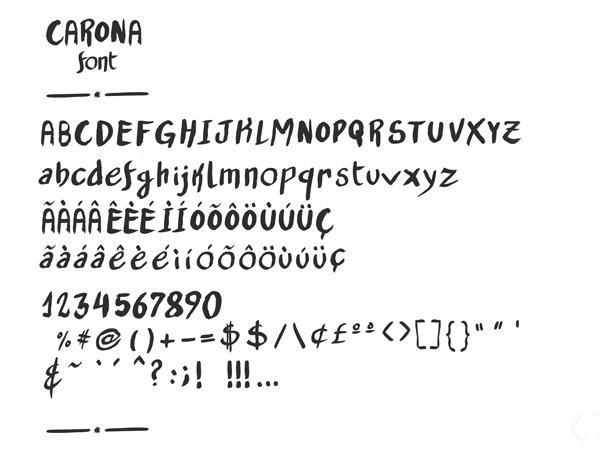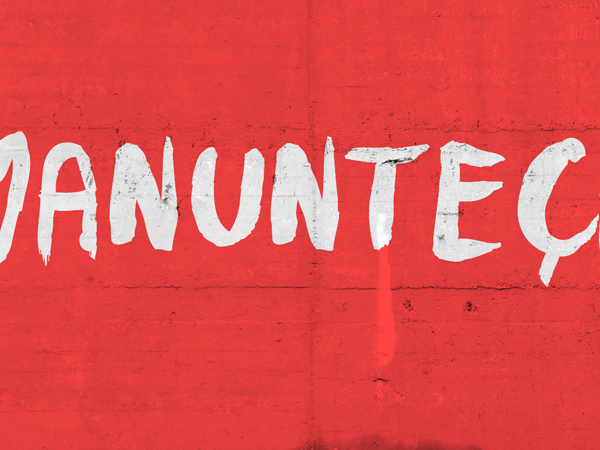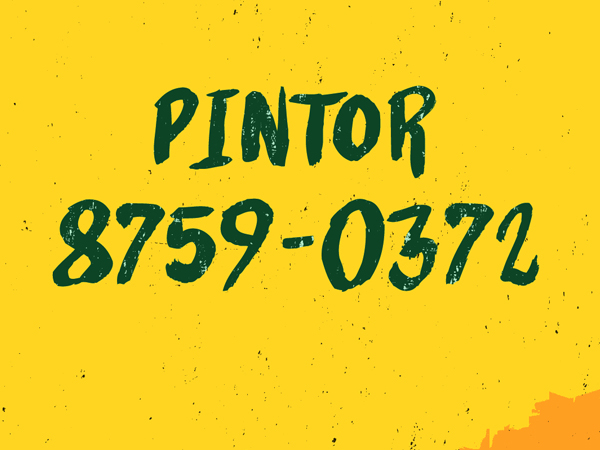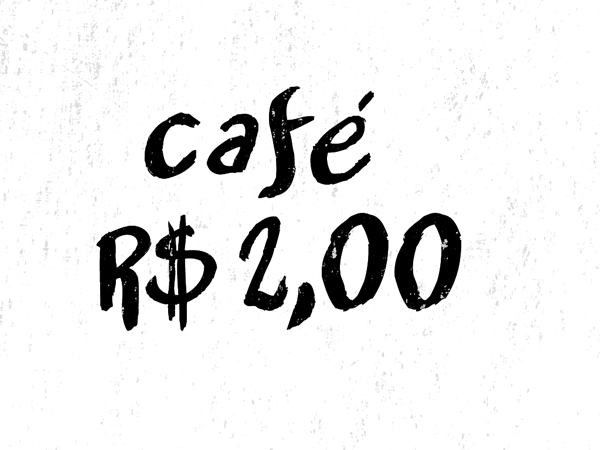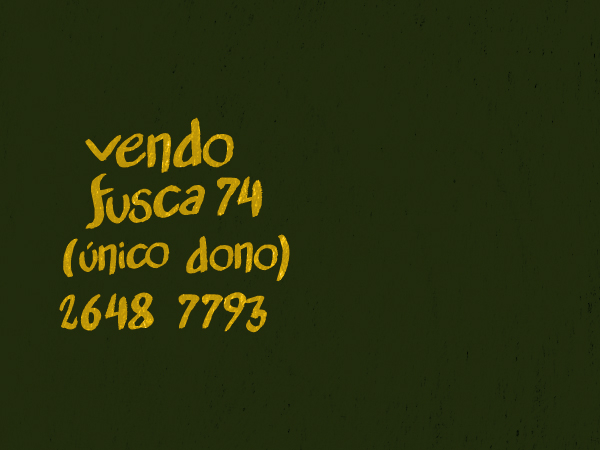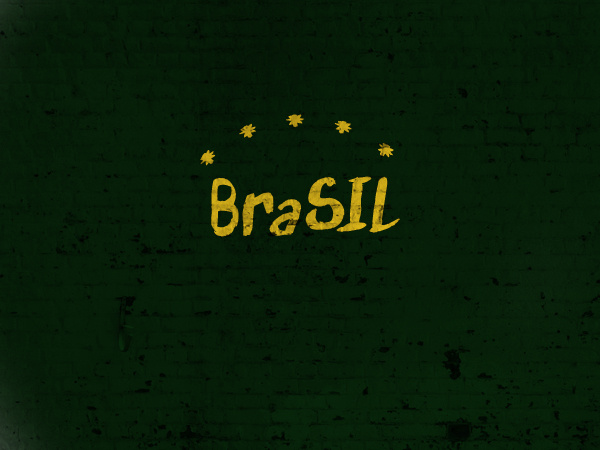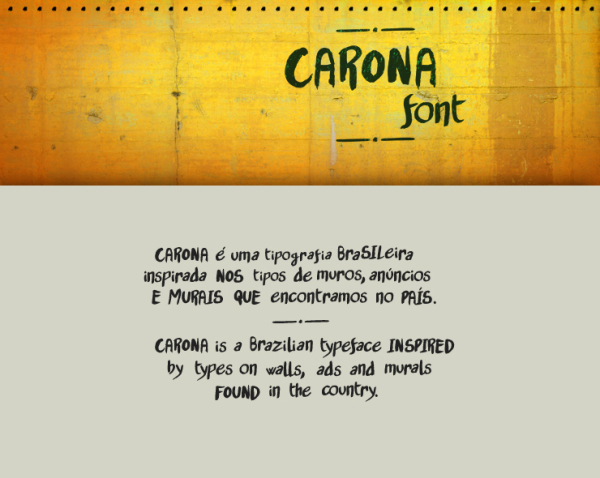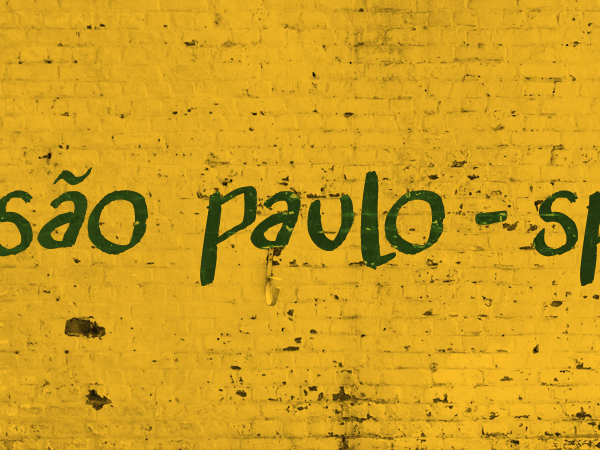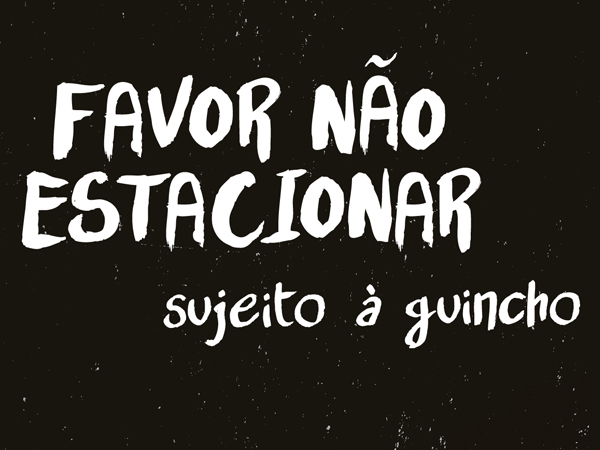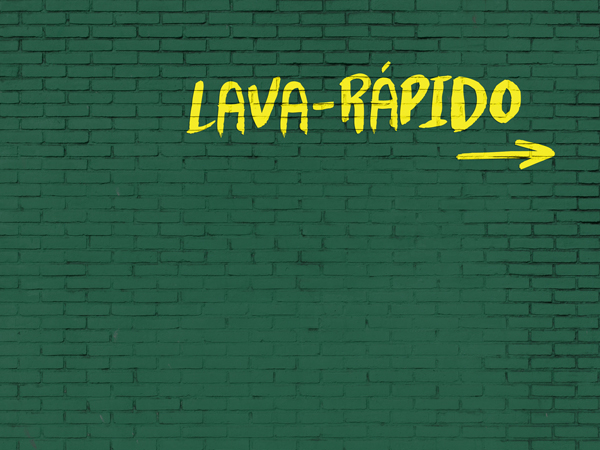
Carona
Carona é uma tipografia brasileira inspirada nos muros, anúncios e murais que encontramos no país. A maioria dessas placas que carregam características que foram incorporadas à essa fonte têm, antes de tudo, a função de informar, independente de beleza, erros ortográficos e ergonomia visual.
Carona is a brazilian typeface inspired by types on walls, ads and murals found in the country. Most of these walls carry features that have been incorporated into this type have, first of all, the function of communicate, regardless of beauty, misspellings and visual ergonomics.